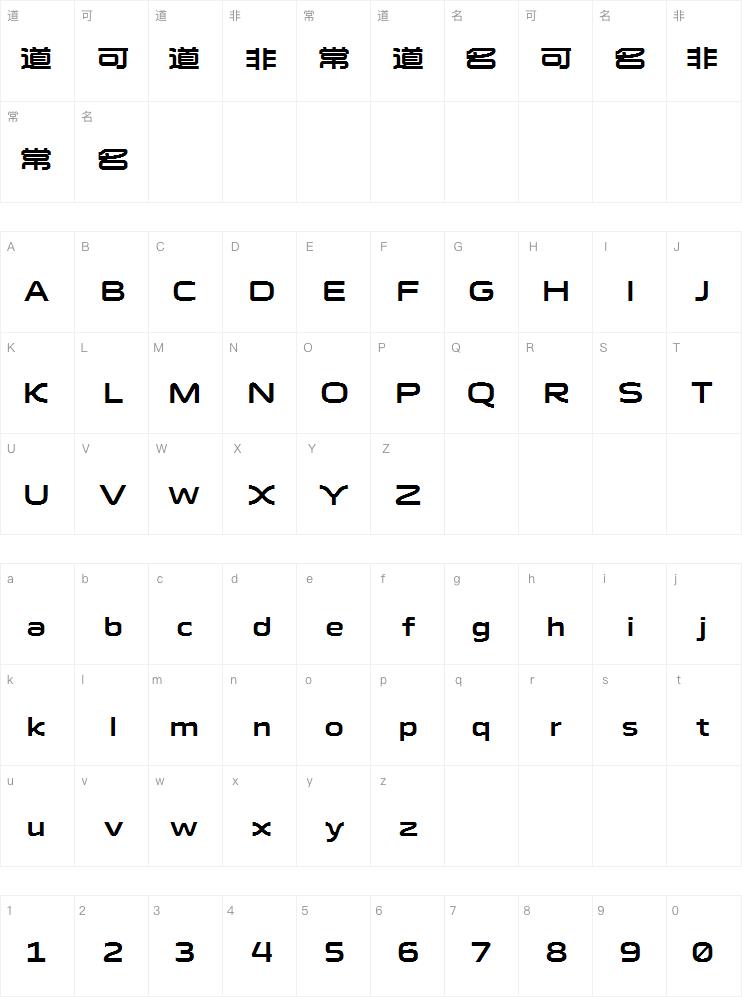
Aa星轨
这款字体对常规汉字笔画进行高度简化与融合,在等粗黑体的基础上以线条化、圆润化手法重构笔画形态。摒弃了繁复设计细节,笔画没有多余的修饰,线条干净利落。字形扁宽,充满力量感。弧线的加入使字体笔画流转自然婉转,强化了整体感,也在厚重的结构中增添了几分灵动韵律。比起由硬朗线条组成的科技力量感字体,这款字体刚柔对比鲜明,展现出复古未来主义美学。这款字体拥有独特的视觉张力,适合作为标题字体使用,应用于时尚潮流品牌、活动运营海报、电商标题、综艺等场景。